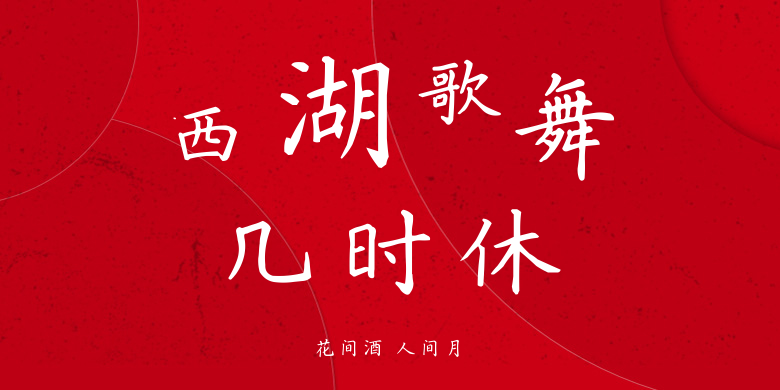
花间酒 人间月
花间酒 人间月,这款字体结构工整、笔画清晰,兼顾美观与易读性,适用于标题、正文、海报、包装、LOGO 等多种场景。字形优雅稳定,风格百搭耐看,适配日常排版与创意设计,让文字呈现更舒适、更具质感。花间酒 人间月一笔一画,皆是细节,以均衡的比例、流畅的线条打造舒适视觉体验,字形端正大气,风格简约现代。无论是商业设计、品牌宣传还是日常排版,都能轻松驾驭,让文字更有格调与力量。花间酒 人间月字体下载。